タイププロジェクト株式会社は、2017年10月2日に学生および教職員が課題や自主制作でフォントを使用するためのアカデミックプランを発表した。
今回のアカデミックプランリリースに対してタイププロジェクトの代表取締役社長、鈴木功氏は「弊社の試作フォント作成ツールであるDrop&Typeを授業で導入いただいている大学から、今度はタイププロジェクトのフォントを使えるようにしたい、という要望をいただいたのがアカデミックプラン提供のきっかけです。より多くの学生や教職員のみなさんに、プロのデザイナーや企業にコーポレートフォントとして採用されているフォントファミリーを使っていただくことで、創作の幅が広がること嬉しく思っています」と述べている。
アカデミックプランでは学生もしくは教職員に対してAXIS Font、AXISラウンド、TP明朝、TPスカイのファミリーを半額で購入できるサービスで、学校の課題や自主制作はもちろん、卒業などの離籍後もそのまま使用でき、商用利用も可能。
利用できるフォント
AXIS Font StdN(スタンダード版)
シンプルで風通しのよいデザインが特徴のAXIS Fontは、正体のベーシックが7ウエイト、長体のコンデンスが6ウエイト、および超長体のコンプレスの5ウエイトからなるバリエーションで、多彩な表現が可能。
AXIS Fontファミリーは、スターバックスやPOLA、としまエコミューゼタウンなどの企業で使用されている。
AXISラウンド StdN(スタンダード版)
AXISラウンドは通常の丸ゴシックとは異なり、内径を丸めていないことにより、モダン・サンセリフのシャープな表情を残している。AXISラウンド50はシャープな輪郭がわずかな丸みを帯び、AXISラウンド100はストロークの先端がほぼ半円の設計になっている。それぞれ7種類のウエイトは、AXIS Fontベーシックの各ウエイトに対応している。
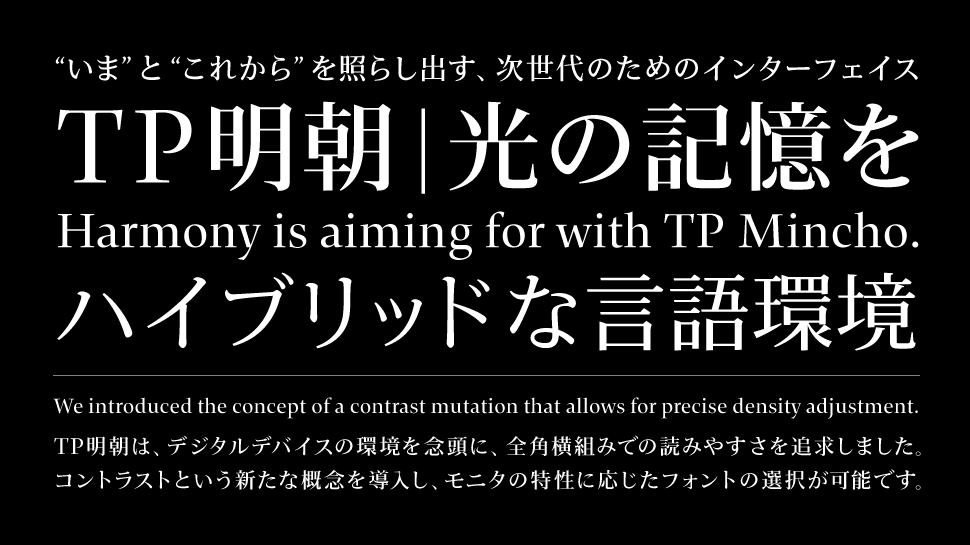
TP明朝 StdN(スタンダード版)
TP明朝は、横画と縦画の太さの比率を自由に変えられるコントラストという概念を導入している。シャープで理知的なハイコントラスト、タフで力強いローコントラスト、そして汎用性の高いミドルコントラスト。各コントラストに6つのウエイトを揃えた。TP明朝は、ブリヂストン美術館の図録や、アニメ「アルドノア・ゼロ」で使用されている。
TPスカイ StdN(スタンダード版)
サンセリフ体に「抑揚」の軸を導入したTPスカイは、スクリーンで効果を発揮するよう設計されたフォントファミリー。アウトラインの滑らかさに重点を置き、アンカーポイントの最小化をはかることで、描画速度における優位性を実現。判読性の向上に有用な3つのコントラスト(ハイ、ミドル、ロー)を備え、それぞれ5つのウエイトを備えている。